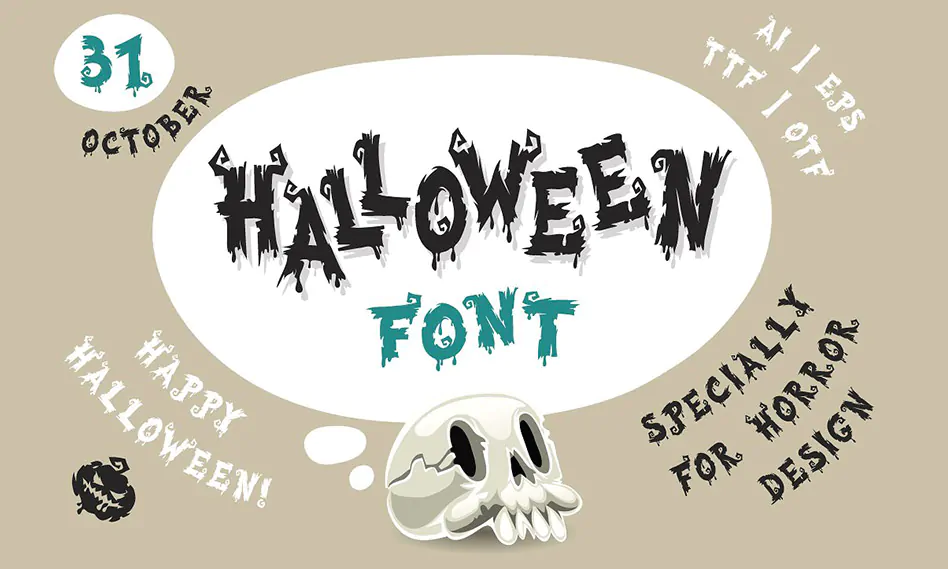
فونت انگلیسی و ترسناک هالووین مناسب برای طراحی و گرافیک
فونت انگلیسی و ترسناک هالووین
در این قسمت از سایت شاهد فونت انگلیسی و ترسناک هالووین مناسب جهت استفاده در طراحی و گرافیک می باشید. فونت هالووین در قالب 2 فایل ttf و otf در سایت قرار گرفته است که با نصب یکی از این دو فرمت در پوشه فونت های سیستم خود قادر به استفاده از آن در تمام نرم افزارهای گرافیکی و ویرایشگر متن از جمله نرم افزار فتوشاپ ، افترافکت ، مجموعه نرم افزار آفیس و … خواهید بود. فونت هالووین در وزن سنگین (Heavy) طراحی شده است که از آن می توان در طرح های گرافیکی همچون طراحی انواع پوستر ، بنر ، تراکت ، بروشور و … استفاده نمود.
- نام فونت : Halloween Voysla
- وزن : سنگین (Heavy)